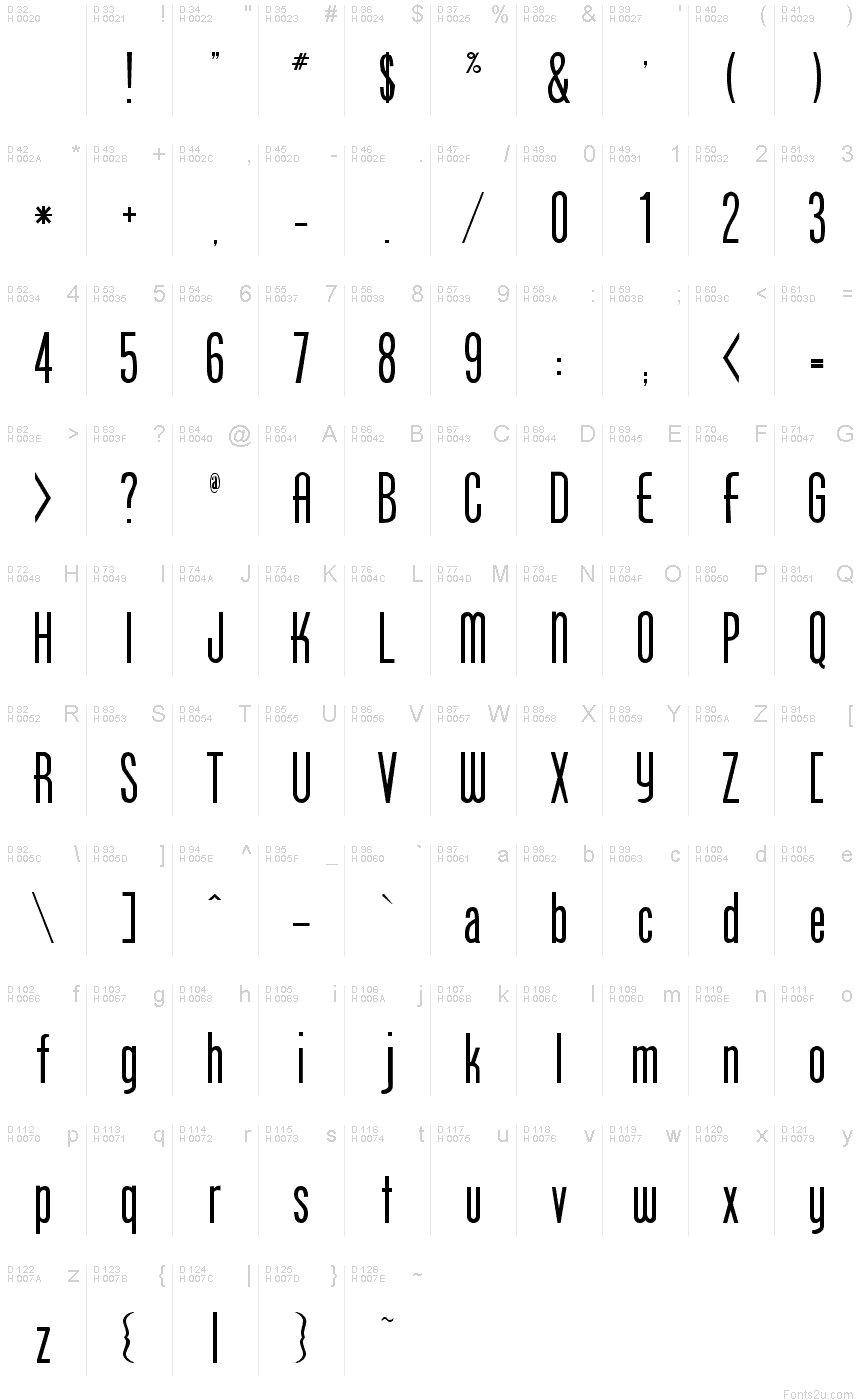
Phoenix autorstwa Van Garretta to darmowy, wąski krój bezszeryfowy o wyrazistym, wysokim, miejskim rytmie. Litery wydają się wyciągnięte w górę i sprowadzone do niezbędnego minimum – z długimi, prostymi liniami, miękkimi łukami i smukłą sylwetką, która nadaje alfabetowi chłodny, plakatowy charakter.
Ten wąski, wyprostowany wygląd sprawia, że jest to naturalny darmowy font do nagłówków, plakatów imprezowych, okładek książek, tytułów i opakowań, gdzie wysokość jest ważniejsza niż szerokość. Świetnie sprawdza się również w krótkich tekstach i brandingowych logotypach, ponieważ liternictwo oparte na wielkich znakach pozwala zmieścić mnóstwo pionowego charakteru w niewielkiej przestrzeni.